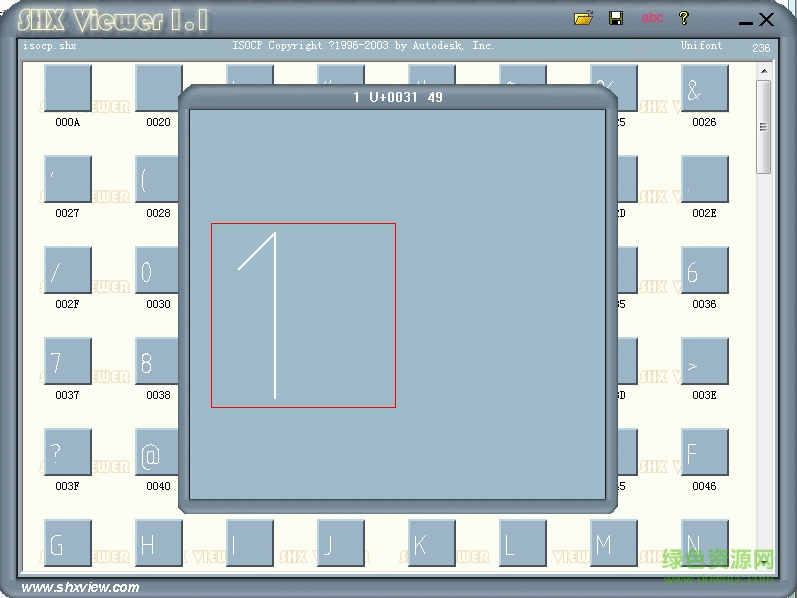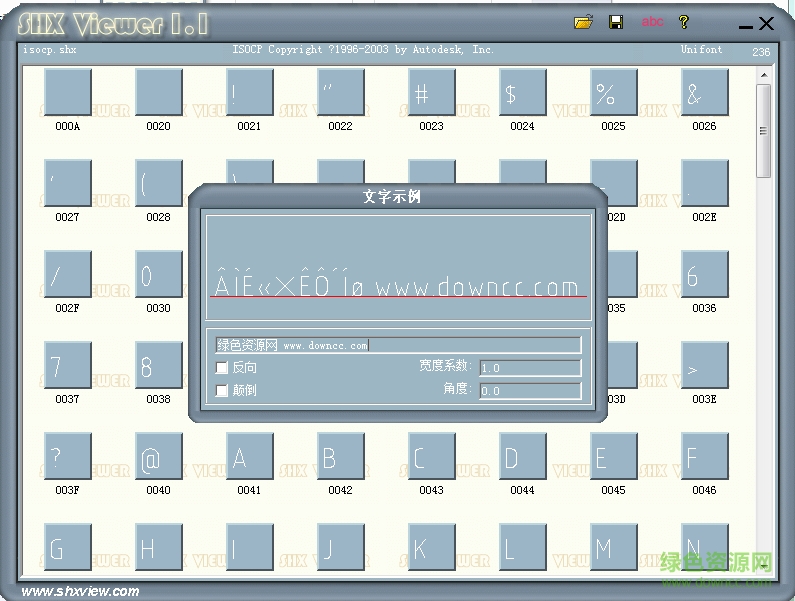
isocp.shx是cad中的一款unifont小字體,支持中文符號(hào)和英文字體,不支持漢字輸入,擁有236個(gè)字符,含有數(shù)學(xué)符號(hào)、希臘字母等,如果您有需要,正在綠色資源網(wǎng)即可免費(fèi)下載!
GB為國(guó)標(biāo),ISO為世界標(biāo)準(zhǔn)
數(shù)字及英文字體:gbeitc.shx 斜體、gbenor.shx 正體、isocp.shx
中文工程字體:gbcbig.shx、仿宋GB_2312.ttf(寬度比例0.7)
autocad提供的Unifont形定義使用十六進(jìn)制形編號(hào),而不使用十進(jìn)制編號(hào)。盡管這并不是必須的,但它使得用/U+控制字符值交叉引用形編號(hào)更加方便。
在一些繪圖規(guī)范中,許多特殊符號(hào)可以出現(xiàn)在文字字符串中。AutoCAD標(biāo)準(zhǔn)文字字體可擴(kuò)展包含特殊字符。然而,擴(kuò)展后的標(biāo)準(zhǔn)文字字體有許多限制,如:
(1) 每個(gè)字體文件的形數(shù)目為255。
(2) 標(biāo)準(zhǔn)字符集使用約一半可用的形編號(hào)。只有代碼1到9,11到31,130到255可用。
(3) 多文字字體需要在每種字體中包含符號(hào)定義的副本。
(4) 特殊符號(hào)需要用戶輸入%%nnn,此處的nnn是符號(hào)的形編號(hào)。
而使用大字體機(jī)制可以避免這些問(wèn)題。用戶可以選擇一個(gè)或多個(gè)不常使用的字符作為換碼代碼,例如使用“|R”來(lái)調(diào)用希臘字母“?!?。
當(dāng)需要在AutoCAD系統(tǒng)中使用大字體時(shí),則要在“Text Style(文字樣式)”對(duì)話框中請(qǐng)選擇“Use Big Font(使用大字體)”選項(xiàng),并在“Big Font(大字體)”下拉列表中選擇所需的大字體文件